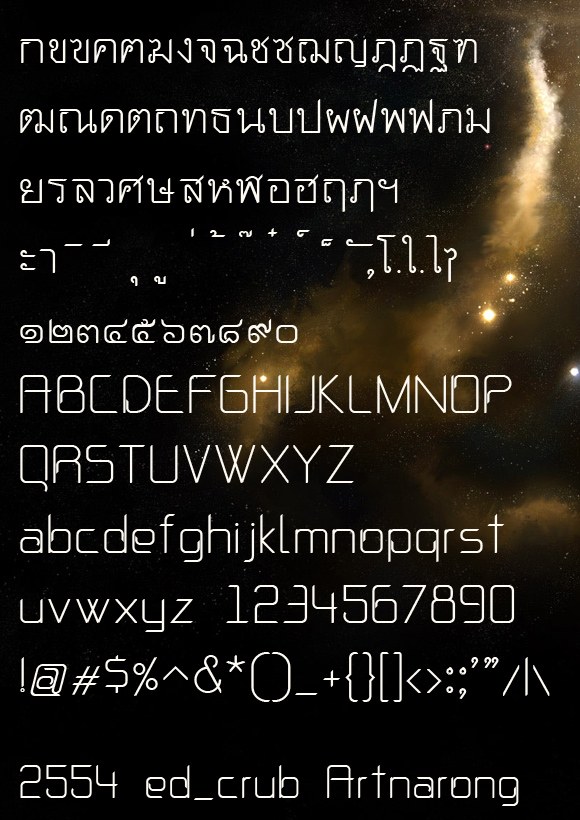
“2554 ed_crub Artnarong” เป็นฟอนต์ตัวที่สองครับ
เอกลักษณ์ คือ เส้นบนตัดตรง หัวกลมแต่ตัดขาดไม่เชื่อมกัน ขลิบปลาย…. (อุ๊ย หวาดเสียว)
ฟอนต์ 2554 ed_crub Artnarong เหมาะกับการเป็นข้อความ(รีเปล่า)
อาจเป็นตัวดิสเพลย์ได้บ้าง (เหรอ) ลองๆ กันดูแล้วกันครับ 😛
2554 ed_crub Artnarong